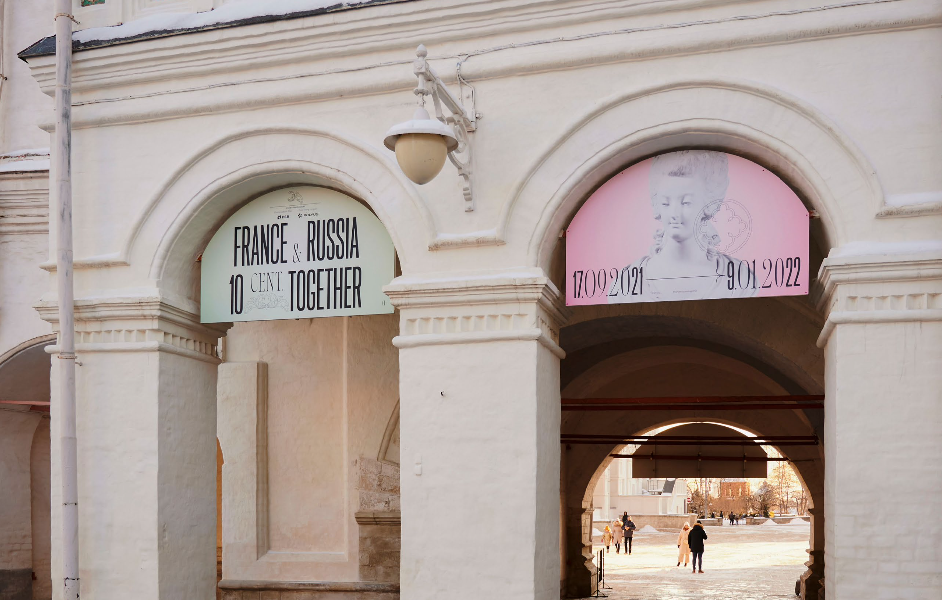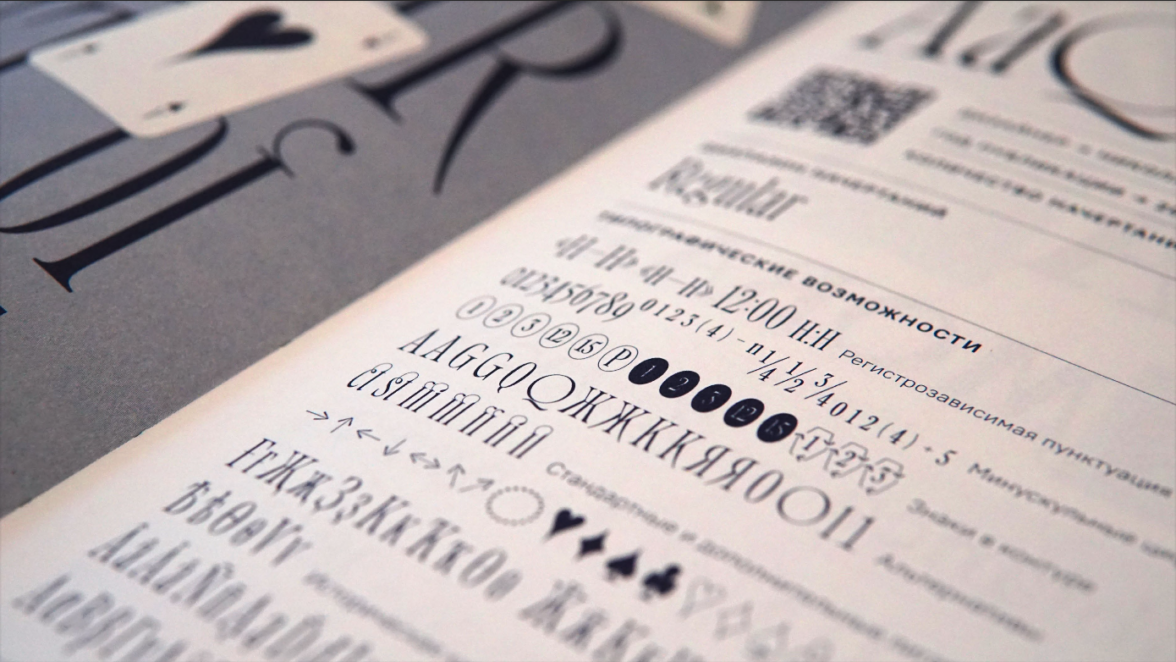
История в буквах: шрифт Helsa Display
Helsa Display черпает вдохновение из шрифтов конца XIX — начала XX века, известных как эльзевиры. Эти шрифты, первоначально использовавшиеся голландским издательским домом XVII века для набора книг Кристофа Плантена, воплощают в себе средне-высокий контраст, острые засечки и характерную шпору у буквы «Р». Однако, как подчеркивает Александра из Paratype, «Helsa — это не историческая реконструкция в буквальном понимании этого слова». Вместо этого, шрифт сочетает заимствованные пропорции и детали с оригинальными элементами, созданными автором, чтобы придать шрифту современный и уникальный характер.
Современная интерпретация
Процесс разработки Helsa Display длился три года — с 2019 по 2022. Николай Недашковский начал с идеи создать современную версию эльзевира, вдохновленную американским шрифтовым каталогом рубежа XIX—XX веков. В итоге, шрифт эволюционировал в нечто гораздо большее, чем просто реконструкция исторического образца, обретя свои уникальные черты и элементы.
Это не шрифт конца XIX или начала XX века — это шрифт нашего времени, созданный с учетом всех особенностей крупного кегля. Он явно не предназначен для мелкого текста, что видно по всем деталям и общему рисунку шрифта — его контуры действительно можно рассматривать как произведение искусства. Помимо стандартных букв, шрифт Helsa включает множество акцентированных символов, разнообразные неалфавитные знаки и поддержку сотни языков, включая греческий и вьетнамский.
Знаковый состав Хельзы — больше 1600 знаков. Кроме букв, там можно найти стрелки, цифры, карточные масти и многое другое.
В интернете шрифт Helsa Display представили как «самобытную компактную антикву с кириллицей и высоким контрастом, которая хорошо подойдёт для заголовков, музыкальных обложек, бренд-дизайна или оформления плакатов».
Завоевывая признание
В 2023 году Helsa Display забрал золото ADCR Awards, а в 2021 стал лицом конкурса «Современная кириллица» — его использовали в каталоге и на сайте конкурса. Шрифт также применялся на выставке музеев Московского Кремля «Франция и Россия: десять веков вместе». Креативной команде приятно видеть свой шрифт в проектах, связанных с культурой, историей, музеями, музыкой, кино, театром, модой.
Александра, являясь не только арт-директором Paratype, но и активным пользователем Helsa, поделилась своим опытом: «Я пользуюсь шрифтом для заголовков в новом издании “Живой типографики”, над которым сейчас работаю, и мне нравится».
Проект Helsa Display — пример того, как традиции могут быть переосмыслены и воплощены в новых формах, соответствующих требованиям и вкусам современности.